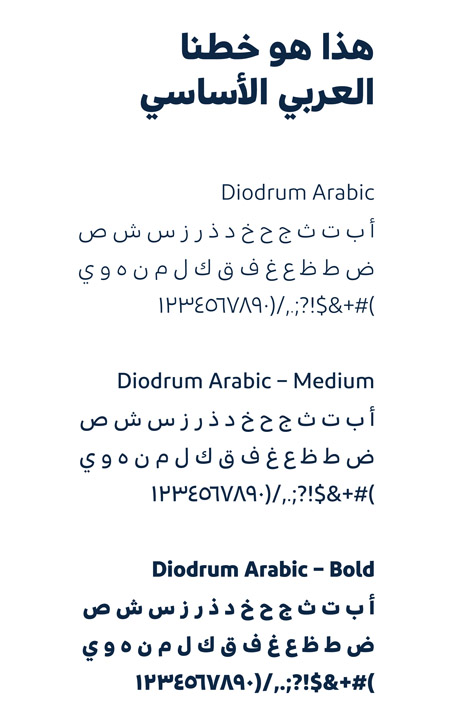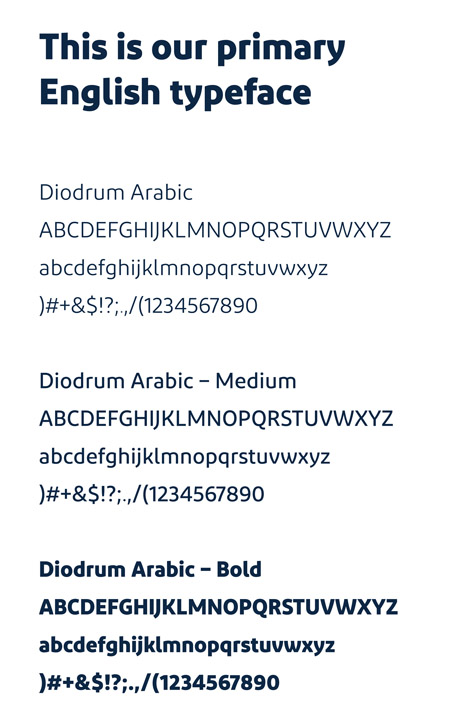
حزمة الخط الطباعي لهوية عام الذكاء الاصطناعي 2026
حزمة الخط الطباعي لهوية عام الذكاء الاصطناعي 2026 .. وهو عبارة عن (3) أوزان باللغتين العربية والإنجليزية، الخط العادي، والخط السمك المتوسط، والخط السميك، ويعتمد الخط الطباعي في هوية عام الذكاء الاصطناعي على الوضوح والحداثة، ويستخدم في مختلف المواد الاتصالية لضمان اتساق الهوية وسهولة قراءتها، ويمكن استخدامه أيضا في أعمال التصميم والدعاية والإعلان والعناوين والنصوص، وهو متاح للتحميل المجاني الآن.